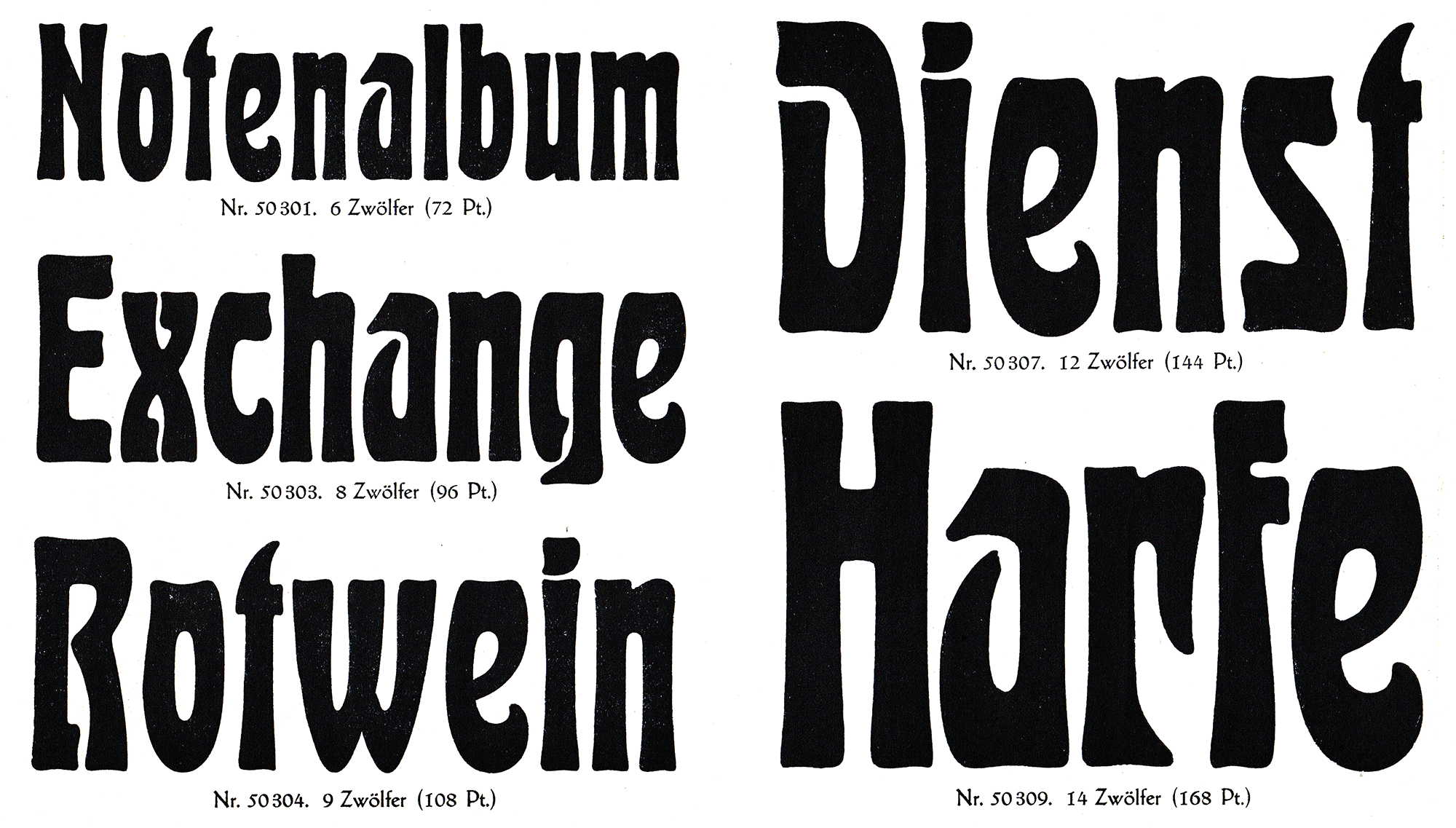
• 1901
• Antiqua dekorativ
Die von Albert Knab entworfene Edelgotisch erschien ab 1901 bei Schelter & Giesecke. Eine schmalfette Version kam 1904 dazu. Ebenfalls verfügbar waren florale Initialen.